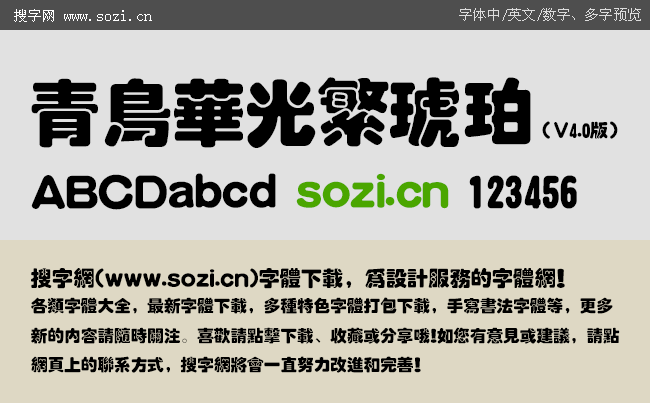
青鳥(niǎo)華光繁琥珀
搜字網(wǎng)給大家提供一款青鳥(niǎo)華光繁琥珀中文藝術(shù)字體下載。青鳥(niǎo)華光繁琥珀是一款設(shè)計(jì)非常復(fù)古具有獨(dú)特韻味的字體,青鳥(niǎo)華光繁琥珀柔滑細(xì)膩,強(qiáng)壯有力,筆畫(huà)清晰醒目?捎卯(huà)冊(cè)設(shè)計(jì)、平面設(shè)計(jì)、印刷包裝、報(bào)紙雜志等廣告設(shè)計(jì)場(chǎng)合使用。
- 風(fēng)格類(lèi)別: 琥珀體